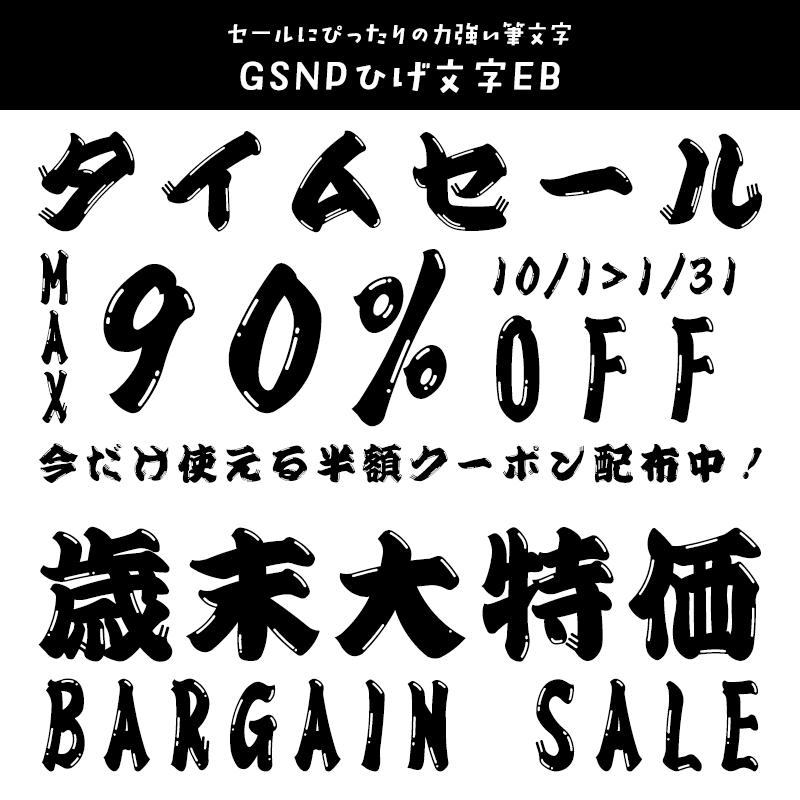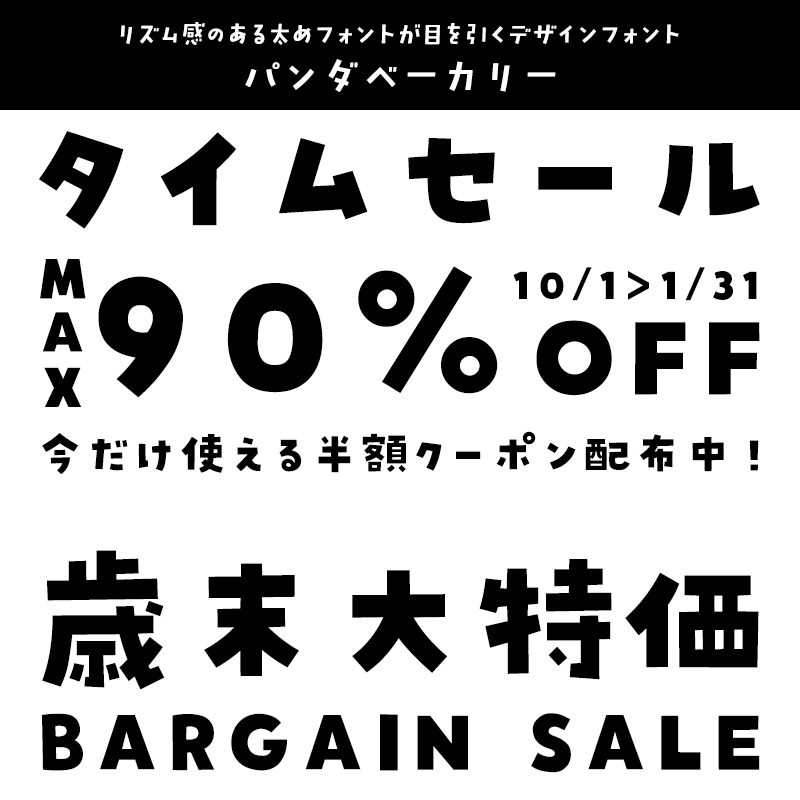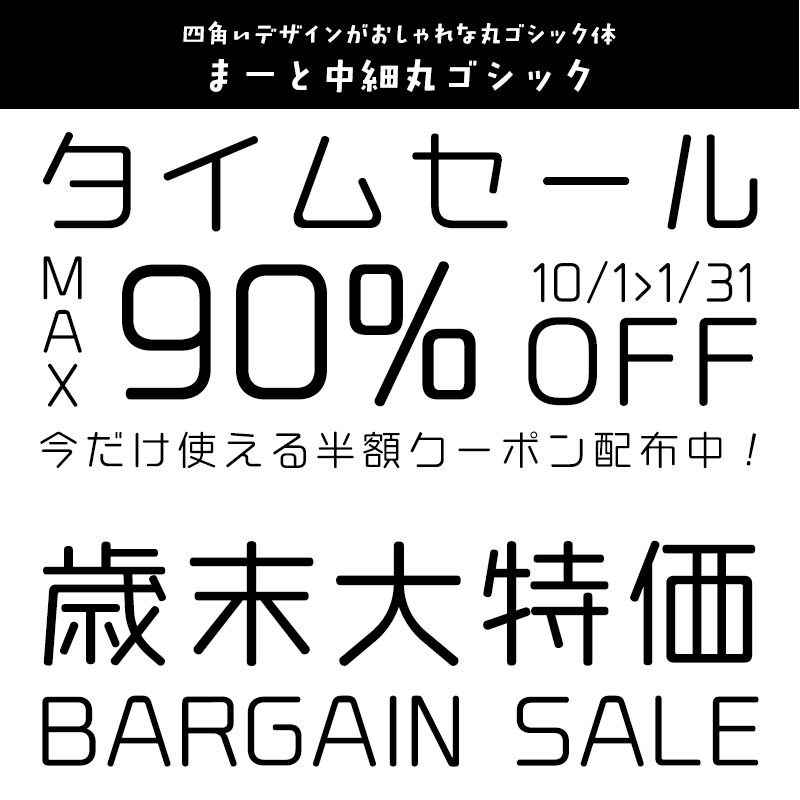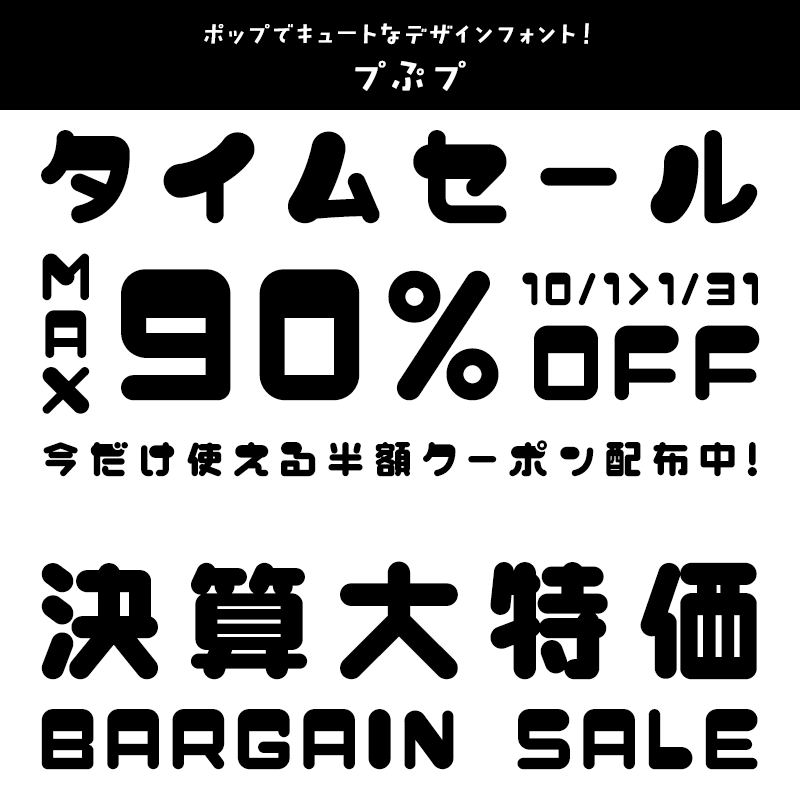
「セール」に合うフォント 特化型 目的別フォントガイド,華やか,躍動感,かっこいい,スタンダード,欧文
「セール」に合うフォント:特化型 目的別フォントガイド #121
フォント取り扱い数 No.1のデザインポケットが、豊富なラインナップの中から一部のニーズに特化した目的別のオススメフォントをご紹介します。
今回は「セール」に合うフォント。日々フォントのことばかり考えている当店スタッフが直感的に選んだフォントをご紹介します。
「セール」に合うフォントをスタッフが選びました
「セール」に合うフォント AR花文字梅U
梅でアレンジされた花文字がおめでたい
▶AR花文字梅U【アーフィック】
「セール」に合うフォント AFCoffee3
古くから使われている花文字を梅でアレンジ、江戸文字がベースとなっているから、年末年始のおめでたい雰囲気にもおすすめです。
「セール」に合うフォント 大髭
セールにかける力強い覚悟を表すにぴったりの毛筆書体
▶大髭【白舟書体】
「セール」に合うフォント 大髭
コンピュータでデザインして仕上げた髭文字ではなく字母を手書きし、さらにその上から昔ながらの方法で髭や虫喰を手書きした、アナログ感溢れる髭文字です。
「セール」に合うフォント AR髭勘亭H
めでたいセールにぴったりの喜び表す髭文字フォント
▶AR髭勘亭H【アーフィック】
「セール」に合うフォント AR髭勘亭H
めでたい行事などに好んで使用される髭文字は寄席文字をベースにされることが多い中、勘亭流をベースとしている珍しい髭文字書体です。かすれがヒゲとして強調され、力強さ、躍動感、喜びを表現できます。
「セール」に合うフォント GSNPひげ文字EB
セールにぴったりの力強い筆文字
▶GSNPひげ文字EB【システムグラフィ】
「セール」に合うフォント GSNPひげ文字EB
勢いを感じる極太の力強い筆文字。セールのチラシやバナー、和風デザインが増える年末商戦の広告などにぴったりです。
「セール」に合うフォント Shorai Sans StdN Bold
シンプルでわかりやすい定番バナーデザインに
▶Shorai Sans StdN Bold【Monotype】
「セール」に合うフォント Shorai Sans StdN Bold
Avenir(R) Nextをベースに開発され、Avenirが持つ幾何学的な形状と、単純明快な線の構成が特徴。バランスの良さと安定感のジオメトリックな日本語サンセリフ体です。細部にまでこだわり、デバイスや媒体を問わず本文でも見出しでも使うところを選ばない書体デザインです。
「セール」に合うフォント 黒基体
圧倒的なインパクトが欲しいデザインに
▶黒基体【楽フォント】
「セール」に合うフォント 黒基体
柔らかさとボリュームのあるゴシック体としての力強さを両立させています。太いのにスッキリした優秀な極太フォント。
「セール」に合うフォント DFひびゴシック体 W14
強烈な価格破壊セールをイメージさせるゴシック体
▶DFひびゴシック体 W14【ダイナフォント】
「セール」に合うフォント DFひびゴシック体 W14
ひびゴシック体は、超極太ゴシック体をベースに、筆画の一部に切り込みを入れることでインパクトある印象にデザインされています。
「セール」に合うフォント パンダベーカリー
リズム感のある太めフォントが目を引くデザインフォント
▶パンダベーカリー【鈴木メモ】
「セール」に合うフォント パンダベーカリー
太めでカクカクっとしたフォルムがカジュアルでかわいいポップなフォントです。
「セール」に合うフォント まーと中細丸ゴシック
四角いデザインがおしゃれな丸ゴシック体
▶まーと中細丸ゴシック 【CFONT】
「セール」に合うフォント まーと中細丸ゴシック
丸ゴシックなのに、直線を意識したフォルムでオリジナリティ溢れる丸ゴシック体。スペースいっぱいにデザインされ、可読性よりユニーク性を強調しました。
「セール」に合うフォント またたびフォント
手書き風の文字とかわいい素材はPOPで大活躍間違いなし!
▶またたびフォント【ゆるてがきこむ】
「セール」に合うフォント またたびフォント
よっぱらいのへろりとした文字をアナログで綴ったフォント。おまけ素材も素材もかわいくて正直使えます!
「セール」に合うフォント 花とちょうちょ
オシャレなSALEに使いたいイチオシの手書き風フォント
▶花とちょうちょ 【鈴木メモ】
「セール」に合うフォント 花とちょうちょ
SNSで話題沸騰中!ペンで右上がりに書いた手書き文字から作った軽やかな手書き風フォント。
「セール」に合うフォント DSきりぎりす
楽しいセールのイメージにぴったりのデザイン書体
▶DSきりぎりす【七種泰史/デザインシグナル】
「セール」に合うフォント DSきりぎりす
トリスのハイボールでもおなじみ、切り文字のような大胆さを持ったデザインシグナルの一番人気のデザイン書体。
「セール」に合うフォント プぷプ
ポップでキュートなデザインフォント!
▶プぷプ【ヤマナカデザインワークス】
「セール」に合うフォント プぷプ
他と差がつく個性派フォントが目立つこと間違い無し。カジュアルな雰囲気を演出したいときにピッタリです。
「セール」に合うフォント まーとオープンボールド
アクセントを入れるときに丁度いい白抜きのフォント
▶まーとオープンボールド 【CFONT】
「セール」に合うフォント まーとオープンボールド
ポップな表情が面白い効果を生むデザインなので協調したい文字に使っていただくと効果的かもしれません。SALEポップの他にも、DTP・WEB・ゲームなど多岐に使用できるフォントです。
「セール」に合うフォント DIN Next™ Pro Bold
SALEチラシに使われる定番欧文フォント その1
▶DIN Next™ Pro Bold【Monotype】
「セール」に合うフォント DIN Next™ Pro Bold
DINとは「ドイツ工業規格」の略称で、道路標識や注意書きに使用されるサンセリフ体。クールな感じを演出する際にも重宝されます。
「セール」に合うフォント Futura® Pro Heavy
SALEチラシに使われる定番欧文フォント その2
▶Futura® Pro Heavy【Linotype】
「セール」に合うフォント Futura® Pro Heavy
ラテン語で「未来」を意味する1927年に発売されたサンセリフ体。近代的、幾何学的なデザインで歴史関係に良く使用される書体です。
「セール」に合うフォント Impact™ Std Regular
SALEチラシに使われる定番欧文フォント その3
▶Impact™ Std Regular【Monotype】
「セール」に合うフォント Impact™ Std Regular
キャッチコピーやタイトルでの使用を想定して作られたサンセリフ体。その名の通りインパクトのあるコンデンスのかかった太字の書体ですが、装飾はなくシンプルで可読性が高いのも特徴です。
「セール」に合うフォント Sabon® Pro Bold
SALEチラシに使われる定番欧文フォント その4
▶Sabon® Pro Bold【Linotype】
「セール」に合うフォント Sabon® Pro Bold
Garamondを参考にしたと言われているセリフ体。柔らかい印象をもっており、シャープで洗練された字形から知的で品の良さを感じるデザインです。
「セール」に合うフォント PL Davison Zip Zip Bold